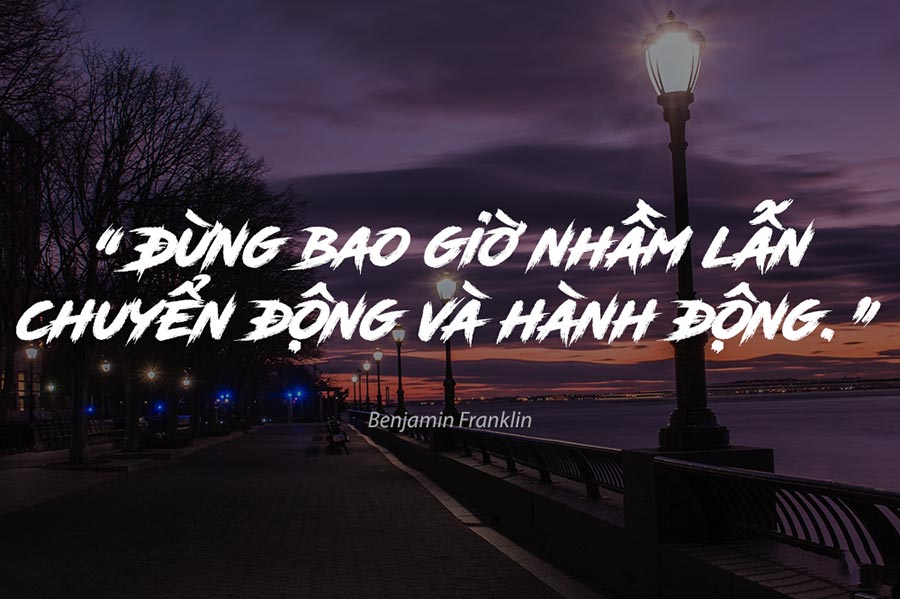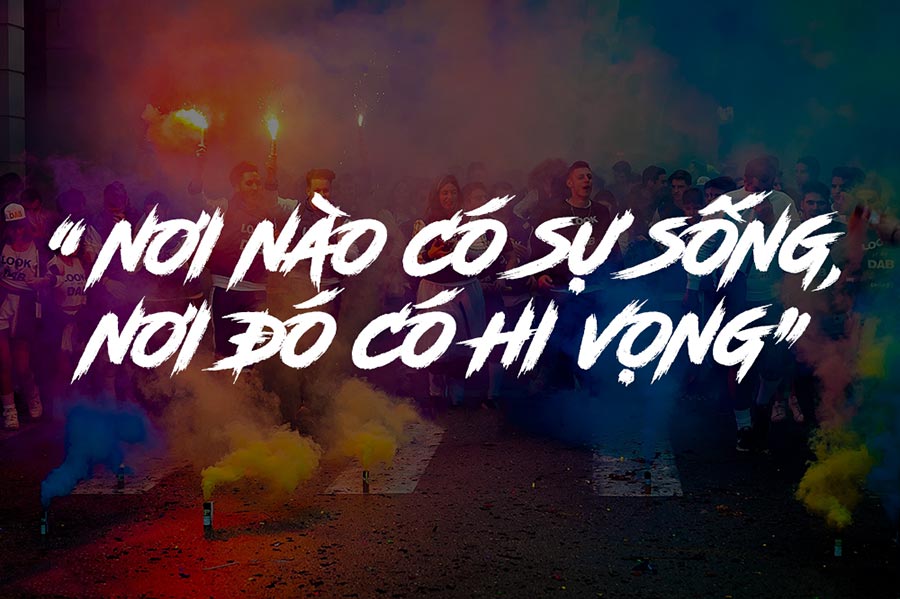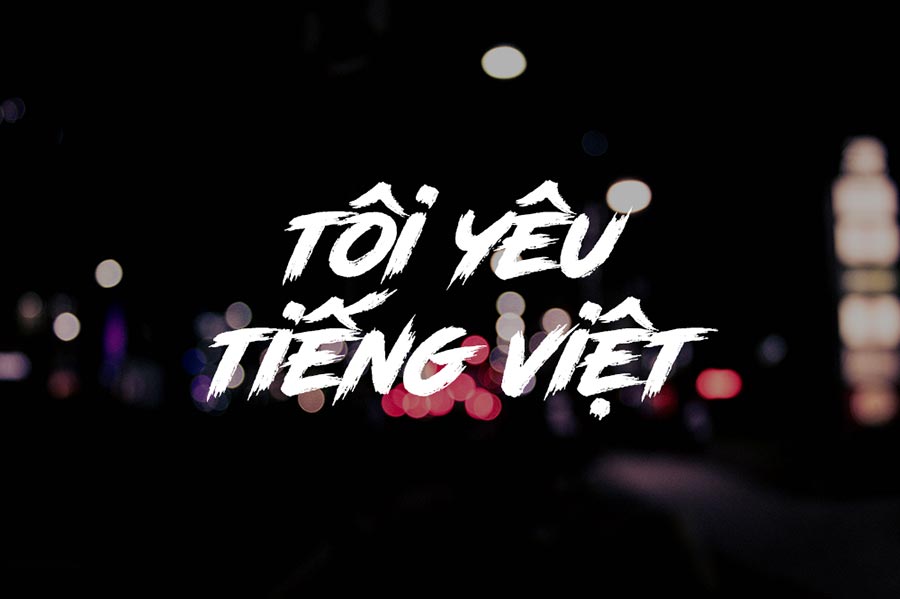
Trong lĩnh vực thiết kế đồ họa, việc sử dụng font chữ phù hợp không chỉ giúp truyền tải thông điệp một cách hiệu quả mà còn góp phần tạo nên phong cách riêng biệt cho sản phẩm. Một trong những xu hướng được ưa chuộng hiện nay là phong cách thiết kế mang hơi thở hoài cổ, đặc biệt là cảm hứng từ thập niên 80. Để hỗ trợ cộng đồng sáng tạo, Sadesign đã chia sẻ miễn phí bộ font Việt hóa SVN mang phong cách này, mở ra cơ hội cho các nhà thiết kế khai thác và ứng dụng trong các dự án của mình.
1. Đặc Điểm Nổi Bật Của Font Việt Hóa SVN Phong Cách Thập Niên 80
Font Việt hóa SVN được thiết kế dựa trên những đặc trưng nổi bật của thập niên 80, bao gồm sự kết hợp giữa màu sắc neon rực rỡ, đường nét phóng khoáng và cảm giác hoài cổ. Bộ font này không chỉ mang lại vẻ ngoài độc đáo mà còn được tối ưu hóa để hỗ trợ đầy đủ các ký tự tiếng Việt. Điều này giúp các nhà thiết kế dễ dàng ứng dụng trong nhiều loại hình dự án khác nhau từ poster, banner, đến các sản phẩm in ấn hay giao diện kỹ thuật số.
Một số đặc điểm nổi bật của font phong cách này bao gồm:
• Hỗ Trợ Đầy Đủ Tiếng Việt: Bộ font được Việt hóa hoàn chỉnh, đảm bảo tính thẩm mỹ và dễ đọc cho người dùng.
• Phong Cách Retro: Tái hiện tinh thần của thập niên 80 với các đường nét đậm, hình khối góc cạnh và cảm giác hoài cổ.
• Dễ Dàng Ứng Dụng: Phù hợp với nhiều loại dự án thiết kế như quảng cáo, thời trang, âm nhạc, và các sản phẩm nghệ thuật khác.
2. Ứng Dụng Của Font Việt Hóa SVN Phong Cách Thập Niên 80
Font phong cách thập niên 80 không chỉ mang tính thẩm mỹ mà còn giúp tạo nên sự khác biệt trong các sản phẩm sáng tạo. Dưới đây là một số ý tưởng ứng dụng:
- Thiết Kế Poster Sự Kiện: Với sự nổi bật và thu hút, font này rất phù hợp để sử dụng trong các poster quảng bá sự kiện âm nhạc, triển lãm hay hội chợ.
- Thời Trang Và Bao Bì Sản Phẩm: Các thương hiệu thời trang hoặc sản phẩm tiêu dùng có thể tận dụng phong cách retro để tạo dấu ấn riêng.
- Thiết Kế Giao Diện Web Và App: Font chữ này có thể được sử dụng để làm nổi bật các tiêu đề hoặc điểm nhấn trong giao diện kỹ thuật số.